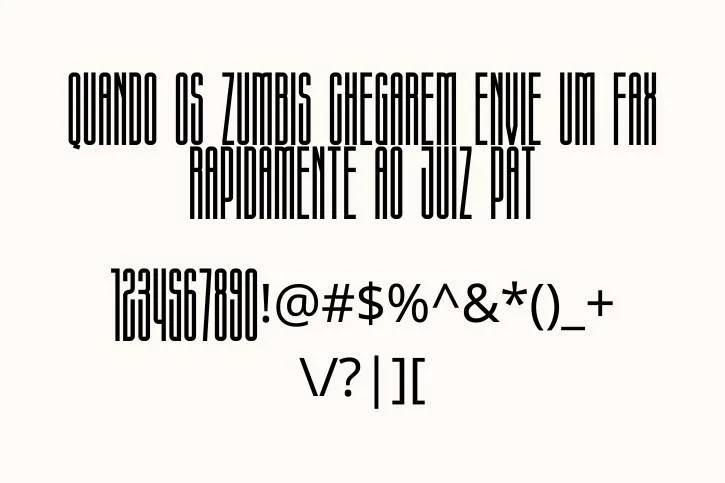
A fonte Calcio é uma escolha moderna e versátil para uma variedade de projetos de design gráfico e editorial. É uma fonte sem serifa, projetada por Graphicfresh. Apresenta uma estética clean e contemporânea, ideal para transmitir uma sensação de profissionalismo e modernidade. Seus personagens são desenhados com linhas retas e uniformes, conferindo-lhes uma aparência nítida e elegante.
É apropriado para combinar com suas fontes familiares, como a Fonte The Light, que é uma fonte semelhante. Com uma variedade de pesos e estilos, oferece grande flexibilidade de design. Desde títulos atraentes até texto fluido de fácil leitura, ele pode se adaptar facilmente a diferentes contextos e necessidades de design. Além da funcionalidade, também possui uma estética visualmente atraente.
A legibilidade é sua principal característica. Seus caracteres são projetados para garantir uma leitura clara e confortável, mesmo em tamanhos menores ou em condições de iluminação desafiadoras. Seus caracteres bem proporcionados e espaçamento equilibrado criam uma aparência harmoniosa e agradável.
Exibição da Fonte Calcio
Melhores Recursos da Fonte Calcio
Uma de suas principais características é a variedade de gramaturas e estilos, que oferecem flexibilidade e versatilidade para diversos tipos de projetos. Também possui espaçamento cuidadosamente ajustado entre os personagens, garantindo uma aparência coesa e harmoniosa.
Combiná-la com a fonte Gambero tornará os designs mais elegantes. Outra característica importante é sua excelente legibilidade. Os personagens são desenhados com atenção aos detalhes, garantindo uma leitura clara e fácil. Possui uma estética moderna e contemporânea, com linhas limpas e proporções bem equilibradas.
Família de Fontes per Calcio
- Calcio Regular
- Calcio Bold
Qual é a origem da fonte Calcio?
A fonte Calcio é uma fonte geométrica moderna sem serifa, projetada pela Graphicfresh.
Qual é a melhor característica da fonte Calcio?
Apresenta uma estética clean e contemporânea, ideal para transmitir uma sensação de profissionalismo e modernidade.